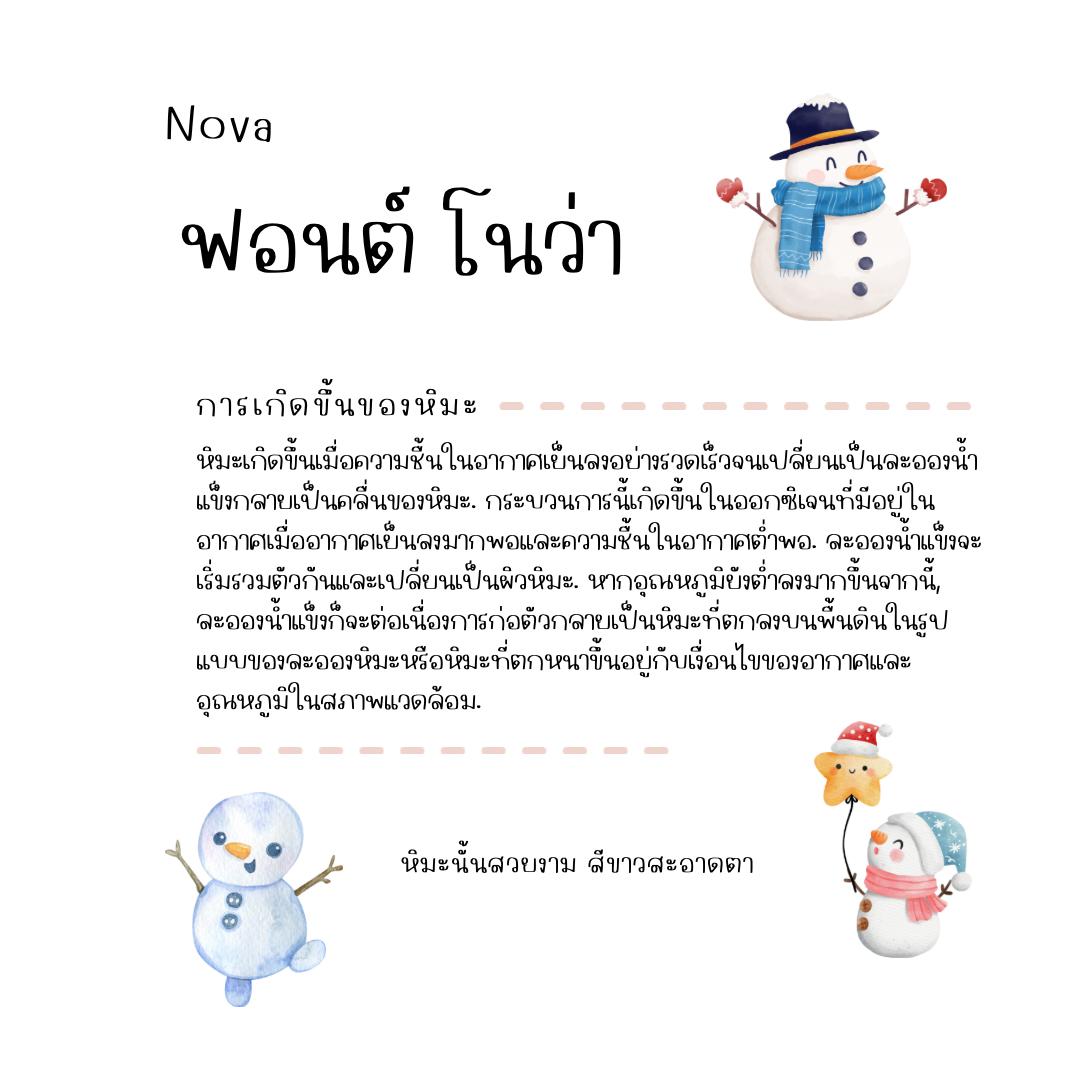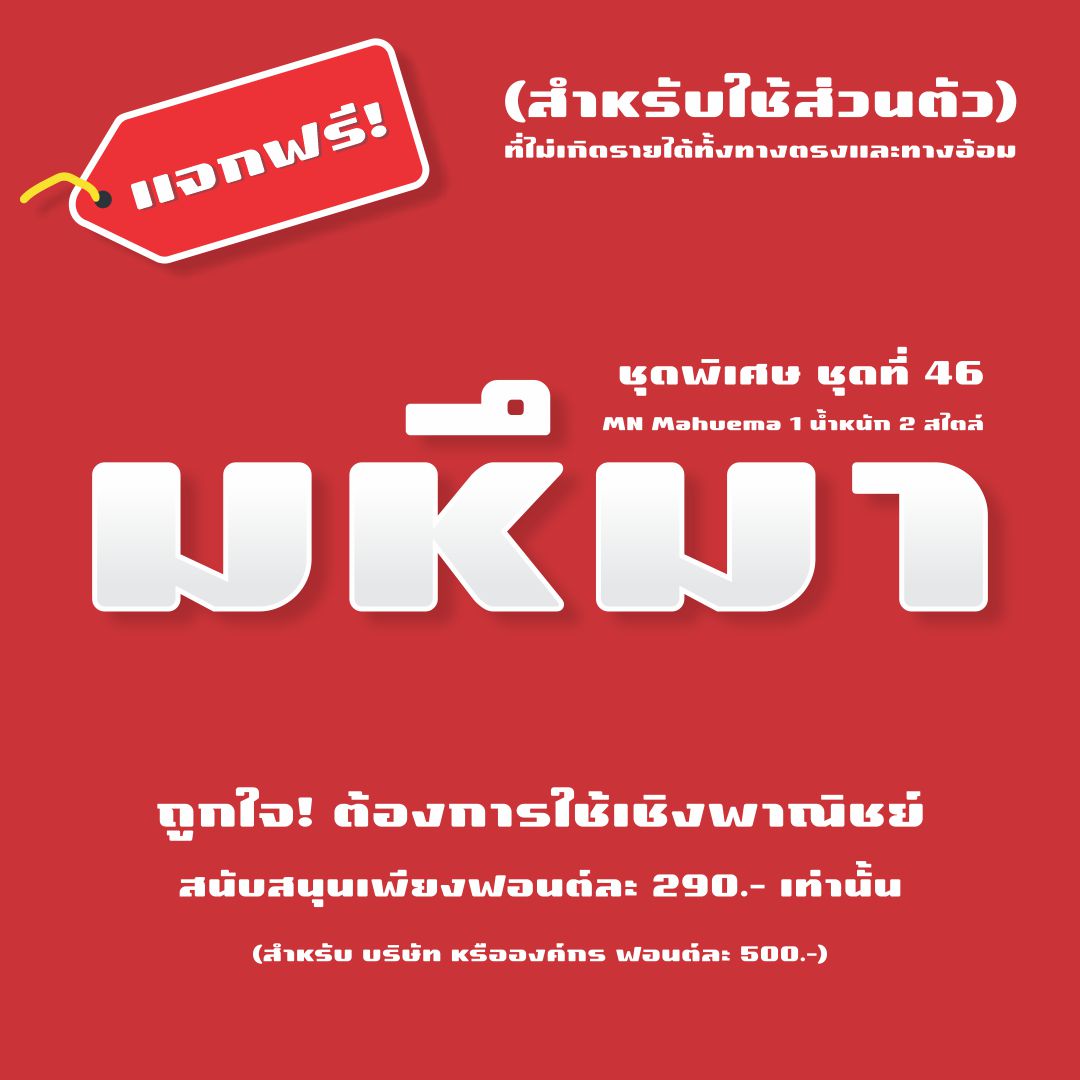
Nova (โนว่า) ฟอนต์ที่มีเอกลักษณ์ ใช้ทำงานสไตล์น่ารักๆ จดโน้ต หรือจะทำแฟลชการ์ดก็ดูดี แจกฟรีไปเลย เวอร์ชันทดลอง : แบบปกติ 1 น้ำหนัก ใช้ได้เฉพาะแบบส่วนตัว เช่น ใช้ในการศึกษา ใช้จด ใช้ตกแต่งสมุดโน้ตตัวเอง
แจกฟรี!!!! ฟอนต์ลายมือ Samba
นูร่ามูนชายน์ (Nura moon shine)
ฟอนต์ลายมือไม่มีหัว มาร์กเกอร์  มีด้วยกัน 3 น้ำหนัก  คือ บาง ปกติ หนา
ฟอนต์ KanchaMay เป็นฟอนต์แนวน่ารัก อ่านง่าย